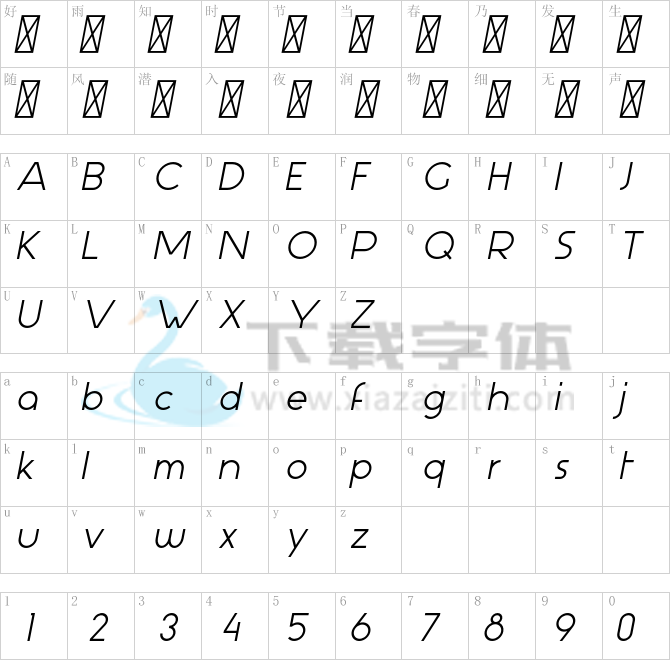
Aspergit.otf字体下载
Aspergit.otf字体下载,这款字体结构工整、笔画清晰,兼顾美观与易读性,适用于标题、正文、海报、包装、LOGO 等多种场景。字形优雅稳定,风格百搭耐看,适配日常排版与创意设计,让文字呈现更舒适、更具质感。Aspergit.otf字体下载一笔一画,皆是细节,以均衡的比例、流畅的线条打造舒适视觉体验,字形端正大气,风格简约现代。无论是商业设计、品牌宣传还是日常排版,都能轻松驾驭,让文字更有格调与力量。Aspergit.otf字体下载字体下载。